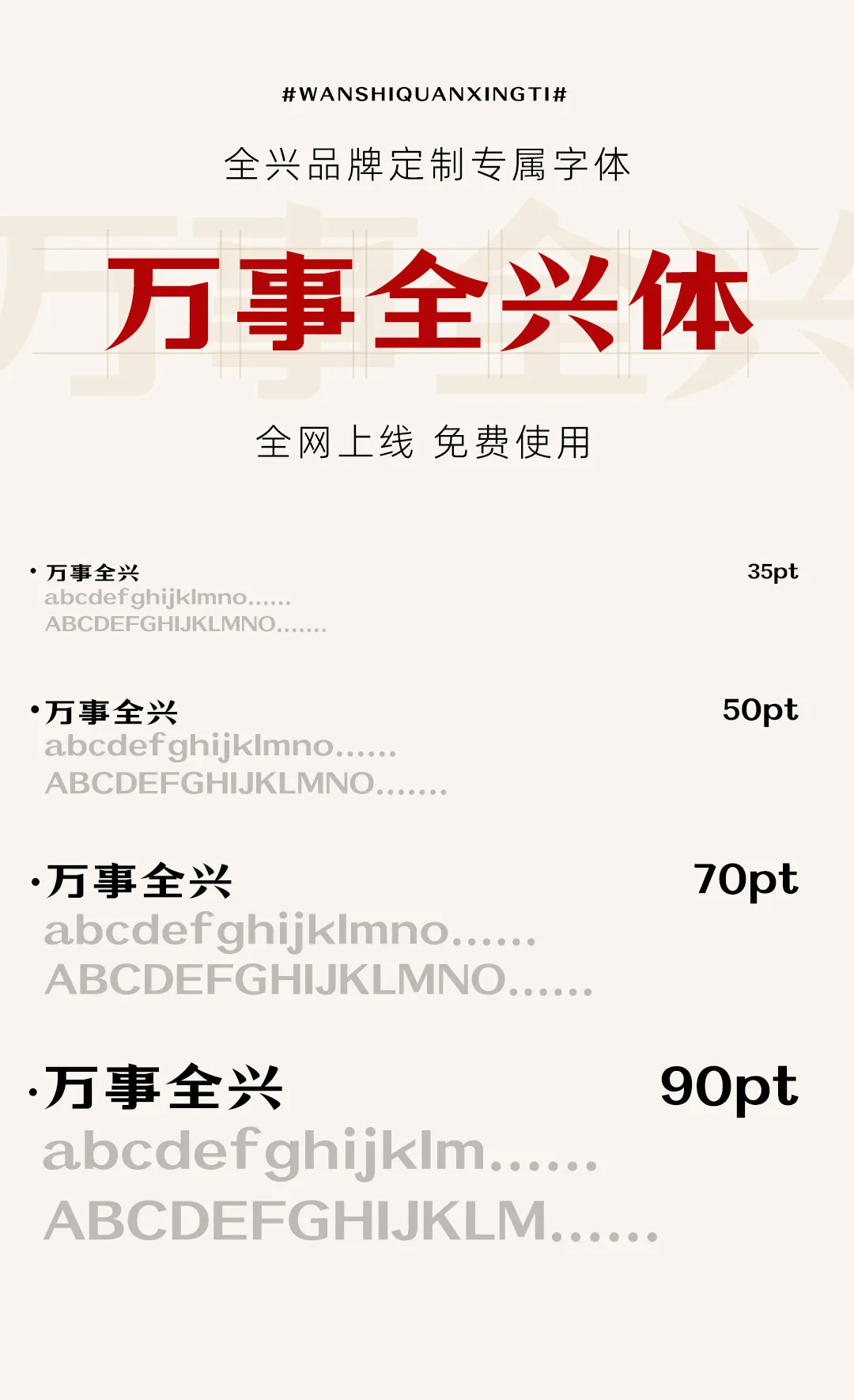
万事全兴体
万事全兴体,这款字体结构工整、笔画清晰,兼顾美观与易读性,适用于标题、正文、海报、包装、LOGO 等多种场景。字形优雅稳定,风格百搭耐看,适配日常排版与创意设计,让文字呈现更舒适、更具质感。万事全兴体一笔一画,皆是细节,以均衡的比例、流畅的线条打造舒适视觉体验,字形端正大气,风格简约现代。无论是商业设计、品牌宣传还是日常排版,都能轻松驾驭,让文字更有格调与力量。万事全兴体字体下载。
全兴品牌定制专属字体
万事全兴体
一笔一划皆风骨点横撇捺显态度「万事全兴体」就算AI再疯狂
贯通融合厚重有力量
脱胎于古典的传统宋体字形经典、优雅,充满人文气息
兼容黑体的笔画特征
疏朗有致,大气简洁
第一印象浑厚庄重同时也不失活力与个性
个性设计气质易拿捏
横竖笔画粗犷有力
粗细对比鲜明,规整有序
撇捺点笔画舒展轻盈收放自如
融入圆角设计亲切自然,温和柔润
刚柔并济,藏露兼备
展现圆融有力、从容进取气质
灵动百变提升原创力
轻松适应各种应用场景
有效满足甲乙丙丁方的需求这便是「万事全兴」的意义